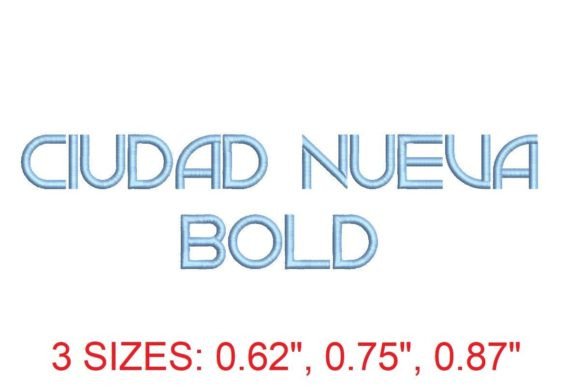
Ciudad Nueva Bold Embroidery Font
Ciudad Nueva Bold Embroidery Font gibi yüksek kaliteli varlıklar arıyorsanız, bu premium paket yaratıcı projeleriniz için harika bir seçimdir.
Hassasiyetle hazırlanan Ciudad Nueva Bold Embroidery Font, temiz vektörler, pürüzsüz tipografi ve içinizin rahat etmesi için ticari bir lisans sağlar.
İster İsteğe Bağlı Baskı (POD) ürünleri, ister düğün davetiyeleri veya sosyal medya grafikleri oluşturuyor olun, Ciudad Nueva Bold Embroidery Font ideal bir uyumdur.